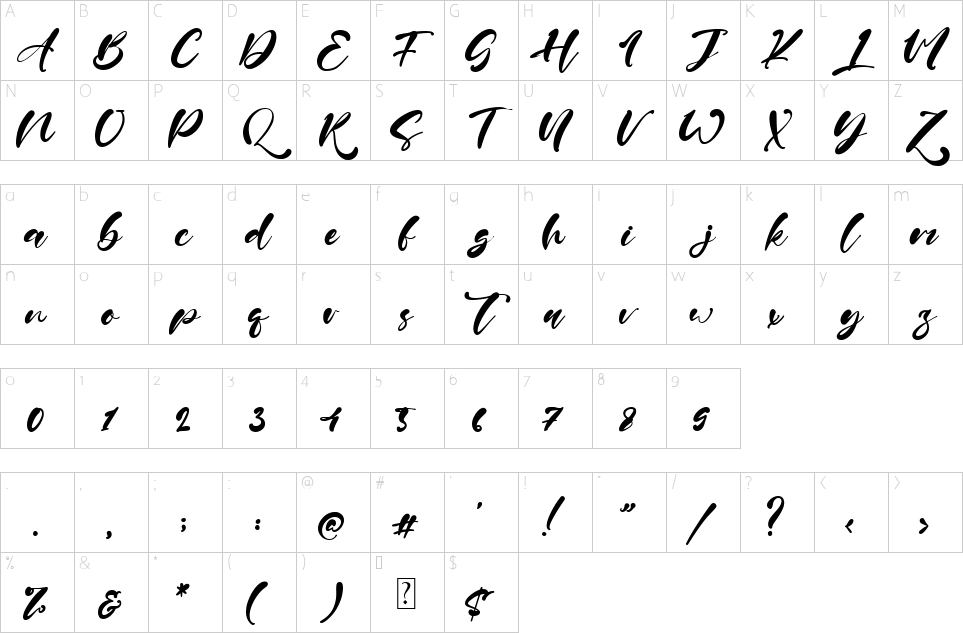
Paul Nora Font | 1001 Free Fonts – Fonte Grátis
A fonte ‘Paul Nora Font | 1001 Free Fonts’ é uma opção perfeita para designers gráficos que buscam uma fonte moderna e elegante. Desenvolvida pelo criador de fontes Font Kong, esta font é ideal para aqueles que buscam uma opção de escrita clara e profissional para projetos digitais. Com 1,983 downloads, a font Paul Nora provavelmente já é conhecida por sua facilidade de uso e sua facilidade em adaptar vários estilos de texto. Seja para títulos ou textos de corpo, esta font oferece uma variedade de opções que vão se adequar a qualquer projeto. A fonte é gratuita, tornando-a ainda mais acessível para designers de todos os níveis. Se você está procurando por uma opção de fonte que possa complementar sua paleta de fontes sem precisar pagar nada, a font ‘Paul Nora’ é um ótimo ponto de partida.